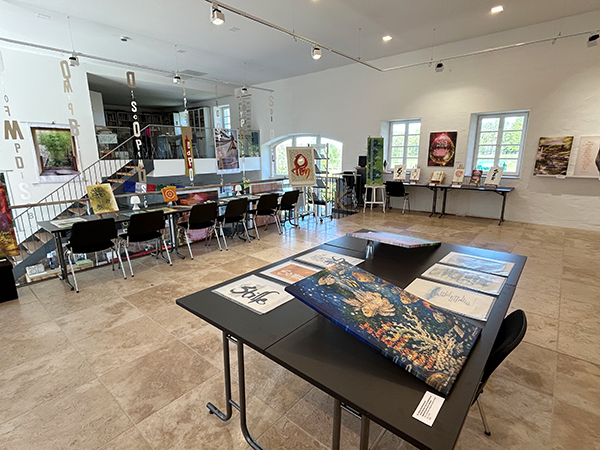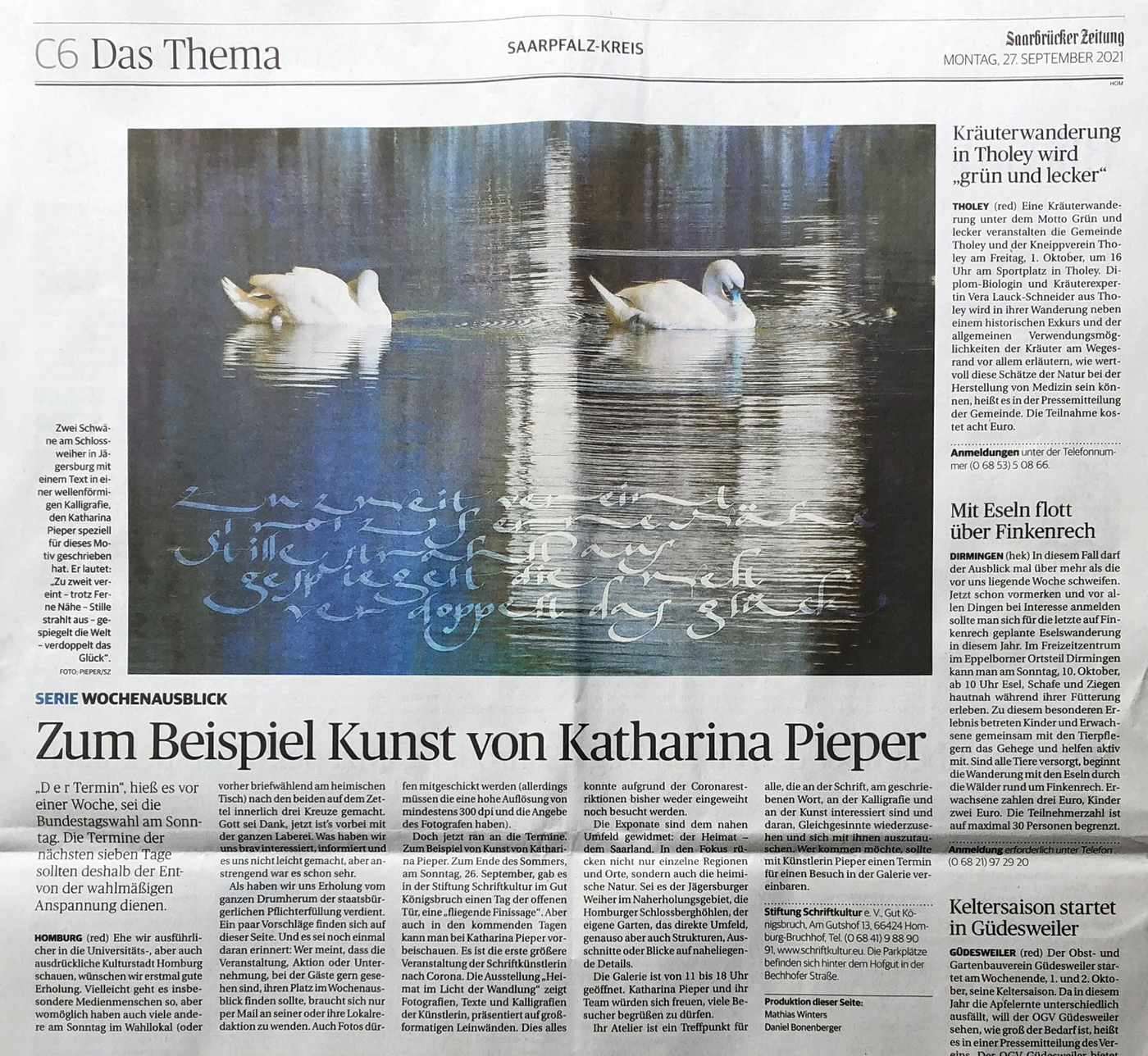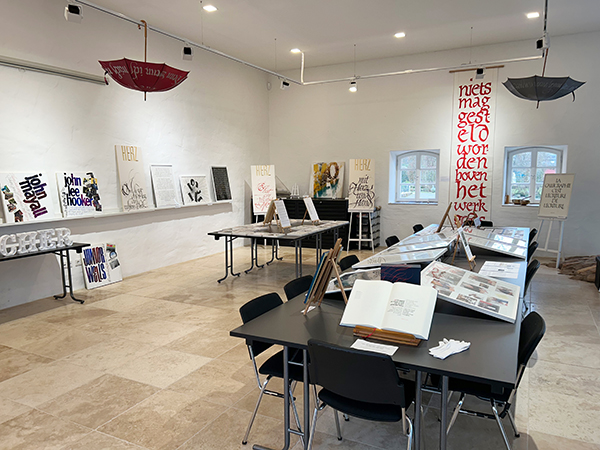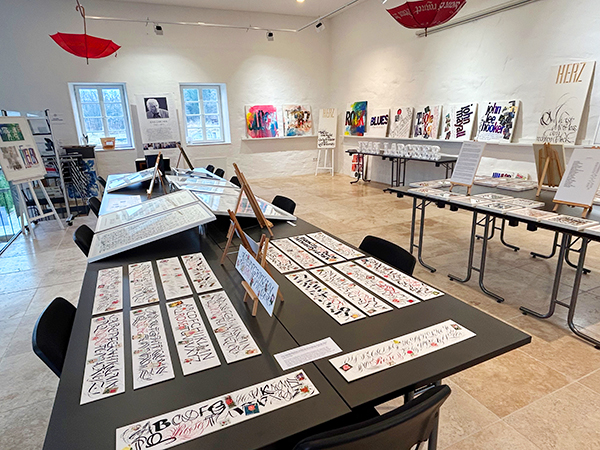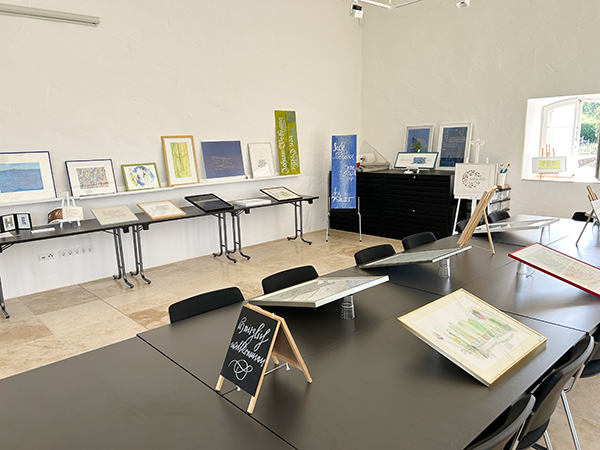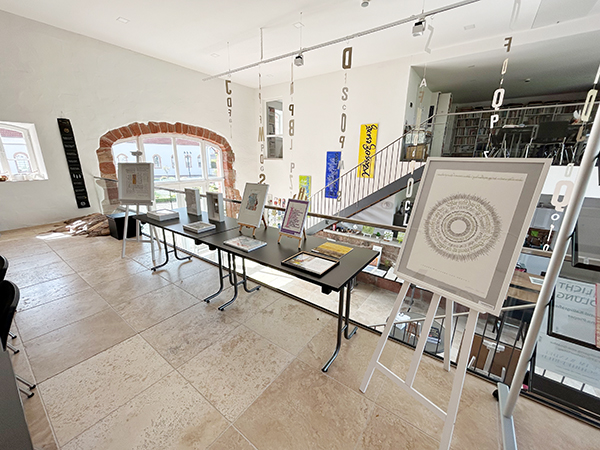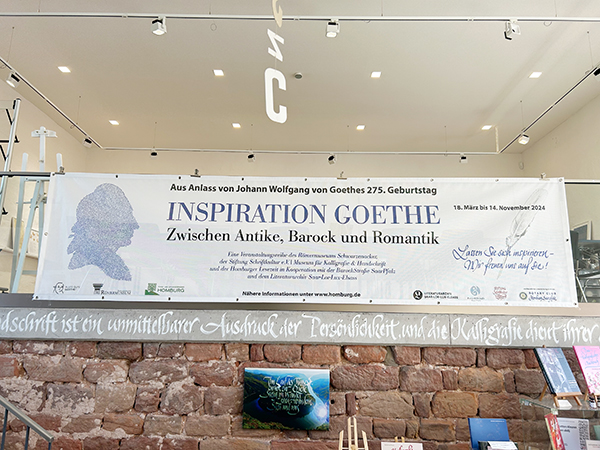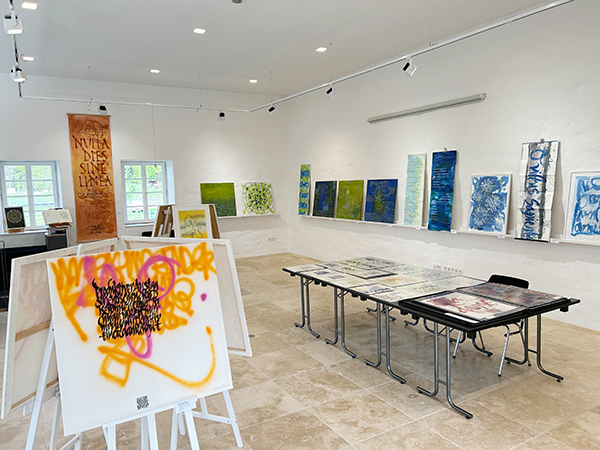
Anhand ausgewählter Werke aus der Ausstellung beleuchtet sie die unterschiedlichen Traditionen
der ostasiatischen und europäischen Kalligrafie. Während in Ostasien Schrift häufig als Bild und
Ausdruck des Augenblicks verstanden wird, steht im Westen die Gestaltung der Schrift
als Träger von Sprache und Kultur im Mittelpunkt. Der Vortrag eröffnet neue Perspektiven
auf die Kunst des Schreibens und lädt dazu ein, Kalligrafie als weit mehr
als schöne Schrift zu entdecken – als sichtbaren Ausdruck von Kultur, Persönlichkeit und Zeit.
Von März 2025 bis November 2025 lief die Ausstellung "Hommage an Jean Larcher – Kalligraf und Lettering Artist"
anlässlich seines 10. Todestages im Jahr 2015. Sie zeigte einen kleinen Überblick über Jean Larchers Werk
aus unterschiedlichen Schaffensperioden.
Einblick in die Ausstellung "275 Jahre Johann Wolfgang von Goethe – Texte im Wandel zum Schrift-Bild"
– Sommer 2024
Einblick in die Ausstellung "Durch die Zeit geschrieben – 40 Jahre Kalligrafie von Katharina Pieper" (2023)
1982 bis 2022
Im September 2022 begeht Katharina Pieper ein besonderes Jubiläum: Sie blickt auf eine vierzigjährige kalligrafische Tätigkeit. Im September 1982 begann sie ihr Studium Kommunikationsdesign an der Fachhochschule Wiesbaden, im Fach Schrift bei Prof. Werner Schneider (1935 – 2022). Der Unterricht bei ihm war für sie wegweisend. Nach dem Studium widmete sie sich hauptberuflich und mit voller Leidenschaft der künstlerischen Schrift und allem, was damit zusammen hängt. Seit 1988 unterrichtet sie Schriftgestaltung an verschiedenen Hoch- und Fachhochschulen, also seit 35 Jahren. Hunderte Studentinnen, Studenten und Schrift-Interessierte waren bei ihr im Unterricht, weltweit. Mit 29 Jahren schrieb sie ihr erstes Buch "Schrift Schreiben", mit 33 Jahren bekam sie ihre erste Gastprofessur an der Fachhochschule Hamburg für die Sommerakademie Pentiment. Sie hat über 20 Bücher und Kataloge geschrieben und gestaltet oder in ihrer eigenen Edition herausgegeben und über 240 Ausstellungen gemacht bzw. daran teilgenommen (Einzel- und Gruppenausstellungen). Gerne blickt sie zurück auf diese spannende, lehrreiche und auch nicht immer einfache Zeit. Der Tod ihres Lebensgefährten Jean Larcher im Jahr 2015 war ein schwerer Schlag. Doch mit der Gründung der Stiftung Schriftkultur e. V. in den Räumen im Gut Königsbruch lebt auch sein Werk weiter. Nun freut sie sich auf die nächsten großen Projekte, die bis 2024 im Raum stehen! Anlässlich des Jubiläums plant sie eine Ausstellung in der Galerie der Stiftung Schriftkultur. Diese wird am Sonntag, den 7. Mai eröffnet. |
Die Ausstellung
Brief-Kunst aus Frankreich –
kreative kalligrafische Briefumschläge von Jean Larcher
***
L'Art postal de France –
Calligraphie originale sur enveloppes de Jean Larcher
wurde am Sonntag, den 13. März 2022, mit einer "Fliegenden Vernissage" eröffnet.
Die Frühjahrsausstellung der Stiftung Schriftkultur widmet sich kalligrafisch gestalteten Briefumschlägen. Jean Larcher (1947 – 2015) war einer der kreativsten Briefeschreiber, den man sich vorstellen kann. Seine nie endende Phantasie, sein Ideenreichtum und seine kalligrafische Meisterschaft haben der Nachwelt und Katharina Pieper nicht nur viele Werke oder sein Buch "Traits de Caractère" beschert, sondern auch zahlreiche künstlerische Briefumschläge. Die schönsten sind seit Sonntag, den 13. März 2022, in der Galerie der Stiftung Schriftkultur zu sehen. Weitere Öffnungstermine der Ausstellung : weitere Termine folgen. Besuche der Ausstellung für Gruppen: nach Vereinbarung. Zur Ausstellung erschien ein Katalog. Hier weitere Informationen |
Der syrische Schriftkünstler, Designer und Innenarchitekt Ayham Najjar wird ab 31. Oktober neue, großformatige Kalligrafien und Malerei präsentieren. Wie in seiner ersten Ausstellung bei uns hat er auch dieses Mal Blattgold geschmackvoll und inhaltsgerecht eingesetzt und sehr schöne Werke auf Leinwand und Holz geschaffen. Bildhintergründe legt Herr Najjar zumeist in Acryl an, anschließend schreibt und zeichnet er in verschiedenen arabischen Schriftstilen philosophische oder poetische Zitate darauf. Während der Ausstellung werden zusätzlich edle Gebrauchsgegenstände aus Glas und Porzellan mit arabischer Beschriftung gezeigt und zum Verkauf angeboten. Die Ausstellung kann dann schon an diesem Sonntag und an den beiden darauf folgenden, 7. November und 14. November, jeweils von 15 bis 18 Uhr besucht werden. Es gibt zur Eröffnung keine Vernissage, sondern zum Abschluss wieder eine Finissage. Sie findet am Sonntag, den 14. November, um 11 Uhr statt. |
beim Aufbau der Ausstellung am 29.10.21
Ab 21. März 2021 wird in der Galerie der Stiftung Schriftkultur die Ausstellung "Heimat im Licht der Wandlung" präsentiert. Katharina Pieper zeigt ganz neue Arbeiten: Fotografien und eigene Texte, kalligrafisch geschrieben, in das Foto "hineinprojiziert" und auf großformatigen Leinwänden ausgedruckt. Die Fotos zeigen saarländische Motive, die nähere Umgebung, die Natur und auch abstrakte Blicke auf Details. Die Texte befassen sich mit den Themen "Wandlung, Veränderung, Metamorphose und Licht" und nehmen direkt oder im übertragenen Sinne Bezug auf die derzeitige Coronakrise. |
Zum Einstieg in die neue Saison und anlässlich eines großen runden Geburtstags von Edda Börner
wurde ab März 2019 die Ausstellung
FASERN UND FORMEN SCHREIBEN TEXTUREN
von Edda Börner und Katharina Pieper
präsentiert.
Hier einige Eindrücke seit dem Einzug im April 2017:
Tag des offenen Denkmals 2017
Vernissage im Mai 2018